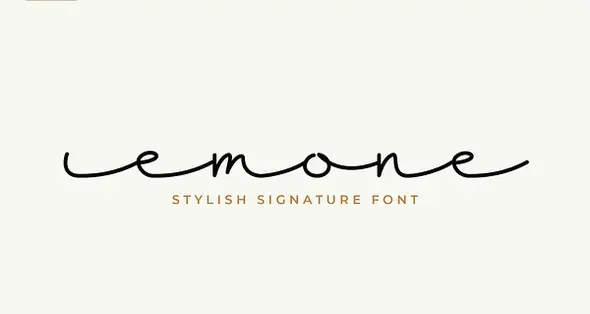
• Emone Script Typeface
فونت انگلیسی دست نویس پیوسته
Emone یک فونت اسکریپت دست‌نویس زیباست که برای آوردن زیبایی دست‌خط طبیعی به دنیای طراحی مدرن خلق شده است. با خطوط سیال، منحنی‌های نرم و سبک امضای ظریف، Emone برای برندینگ شخصی، طراحی لوگو، کارت‌های دعوت عروسی، گرافیک شبکه‌های اجتماعی و بسته‌بندی محصولات که نیاز به حسی شخصی و در عین حال حرفه‌ای دارند، بی‌نظیر است.
این فونت برای لوگوی محصول، لوگوی کارت عروسی، لوگوی برند پوشاک، طراحی‌های وینتیج و بسیاری موارد دیگر عالی است.
Emone is an elegant handwritten script font designed to bring the beauty of natural handwriting into modern design. With its flowing strokes, smooth curves, and refined signature style, Emone is perfect for personal branding, logo design, wedding invitations, social media graphics, and product packaging that need a personal yet professional touch.
This fonts are great for product logo,wedding card logo, clothing brand logo, Vintage design and much more.